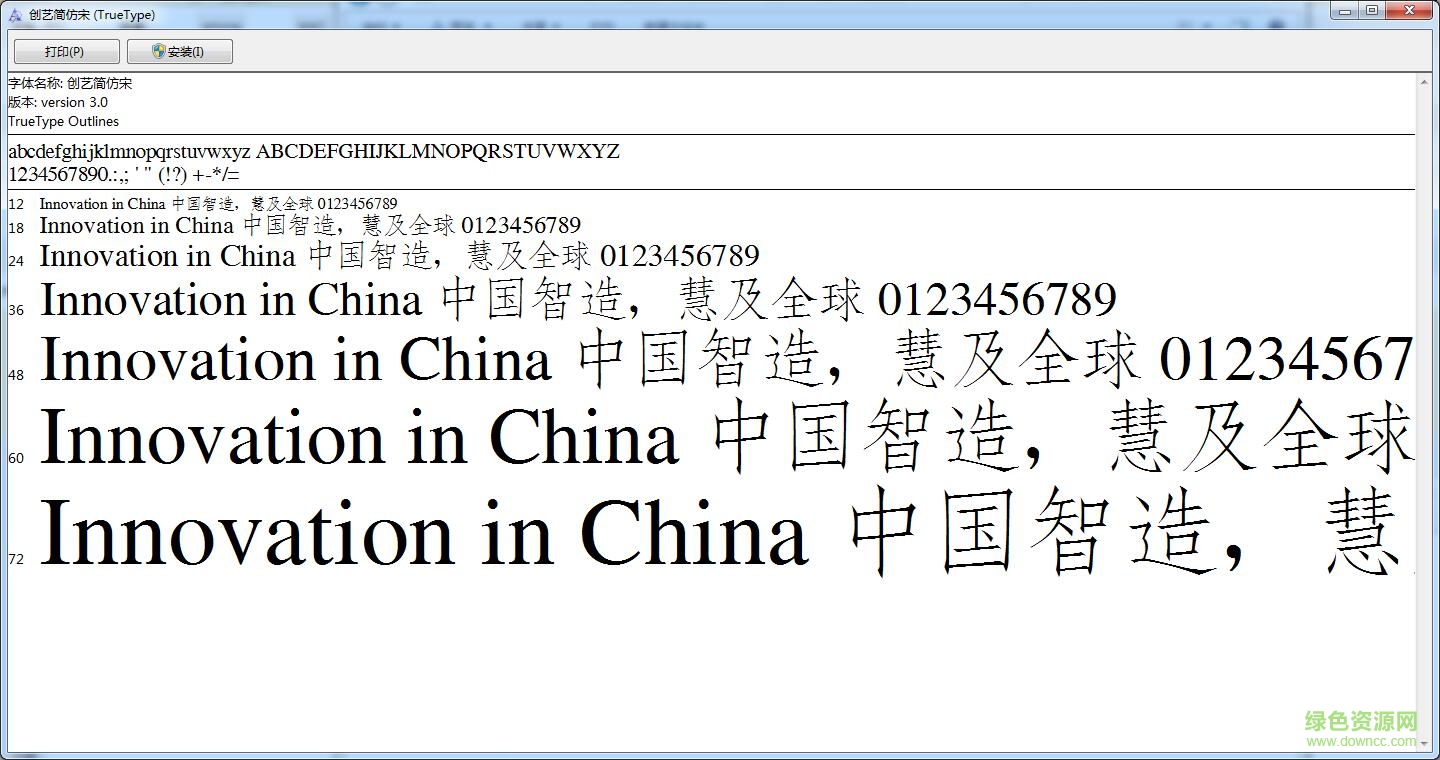
ctfangsongsj是什么字體?ctfangsongsj(創(chuàng)藝簡(jiǎn)仿宋)字體是一款規(guī)范的仿宋字體,字畫清晰,結(jié)構(gòu)緊密,字形清秀,古雅又好看,喜歡這款字體的小伙伴快來免費(fèi)下載收藏吧!
宋體的特點(diǎn)是什么?橫平而豎直,橫筆細(xì)而豎筆很粗,還有每一筆的端點(diǎn)也較粗。
仿宋是印刷字體的一種,仿照宋版書上所刻的字體,筆畫粗細(xì)均勻,有長(zhǎng)、方、扁三體。